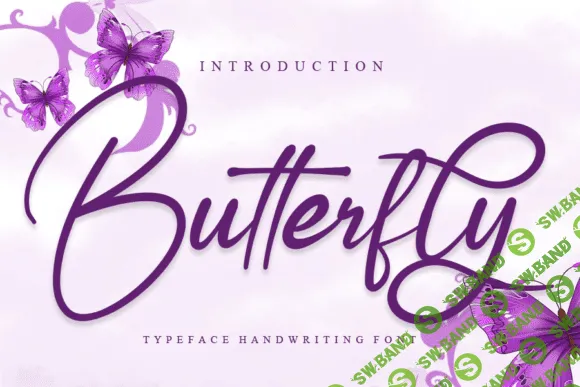
Название: Butterfly Font
[Creativefabrica] Butterfly Font
Butterfly - это стильный и невероятно элегантный шрифт скрипта. Он выглядит потрясающе на свадебных приглашениях, благодарственных открытках, цитатах, поздравительных открытках, логотипах, визитных карточках и любом другом дизайне, который нуждается в рукописном прикосновении.